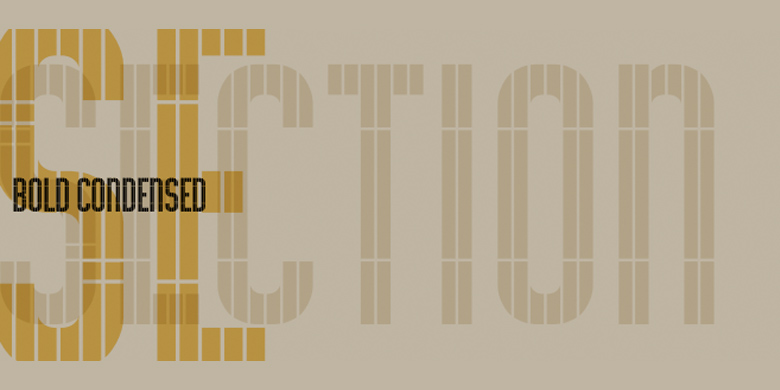
Section
Section,这款字体结构工整、笔画清晰,兼顾美观与易读性,适用于标题、正文、海报、包装、LOGO 等多种场景。字形优雅稳定,风格百搭耐看,适配日常排版与创意设计,让文字呈现更舒适、更具质感。Section一笔一画,皆是细节,以均衡的比例、流畅的线条打造舒适视觉体验,字形端正大气,风格简约现代。无论是商业设计、品牌宣传还是日常排版,都能轻松驾驭,让文字更有格调与力量。Section字体下载。
字体品牌: Monotype 设计师:暂无 字体分类:衬线体 字体属性:外文 字符集:Unicode 发布时间: 2018